Mobile design এখন আর optional না।
Facebook post, YouTube thumbnail, reels cover, poster, banner, quote design—সবকিছুই এখন PixelLab বা অন্য mobile design app দিয়ে করা হয়।
কিন্তু সমস্যা একটাই
👉 সব Bangla font PixelLab-এ ভালো কাজ করে না।
এই পোস্টে আমরা দেখবো:
- PixelLab-এর জন্য কোন Bangla font সবচেয়ে ভালো
- কোন ফন্ট mobile-এ smooth চলে
- কোন ফন্ট headline, poster, caption বা typography-এর জন্য ঠিক
- এবং কোনগুলো avoid করা উচিত
সব কথা সরাসরি, ঘুরপাক ছাড়া।
PixelLab-এ Bangla Font ব্যবহার করার আগে যা জানা দরকার
PixelLab মূলত TTF এবং OTF font support করে।
কিন্তু শুধু format হলেই হবে না, font-এর structure clean না হলে mobile-এ সমস্যা হয়।
PixelLab-friendly Bangla font হলে:
- Unicode based হতে হবে
- Letter spacing balanced হতে হবে
- Stroke বেশি পাতলা বা বেশি মোটা হওয়া যাবে না
- Android-এ crash করবে না
এই কারণেই desktop-এ ভালো লাগা অনেক Bangla font mobile-এ বাজে দেখায়।
Best Bangla Fonts for PixelLab and Mobile Design
নিচে দেওয়া ফন্টগুলো tested, practical এবং Bangladesh-friendly।
1. Noto Sans Bengali
Why it’s great for PixelLab / Mobile Design:
- Very clean and simple
- High readability on small screens
- Works perfectly for headlines, captions, and body text
Best Use:
Minimal poster, quote cards, informative banners
Design Tip:
Medium text size-এ use করলে readability বেশ ভালো থাকে; tiny text avoid করলে result আরও crisp
2. Bangla Lipi Font
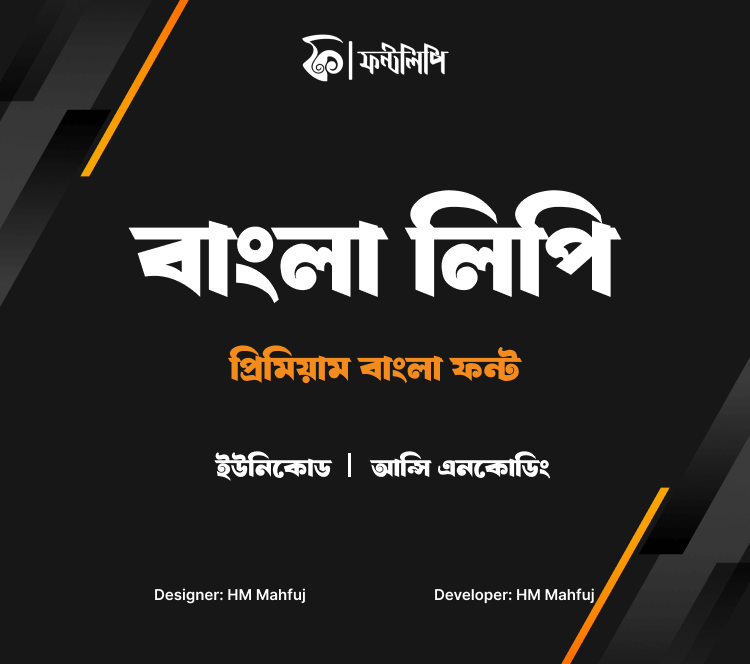
Bangla Lipi Font classic look এবং modern utility দুটোই ধরে রাখে। Serif-like subtle strokes থাকলেও readability modern apps-এ smooth। PixelLab-এ gebruikt করলে vintage yet crisp look মেলে।
Why it’s great for PixelLab / Mobile Design:
- Serif hint, readable texture
- Poster headline & description দুটোতেই useable
- Unicode support keeps mobile rendering safe
Best Use:
Formal event posters, announcement banners, quotes
Design Tip:
Background soft colour হলে text হারিয়ে যাবে না; contrast maintain করলে আরও eye-catching।
3. Amar Praner Modina
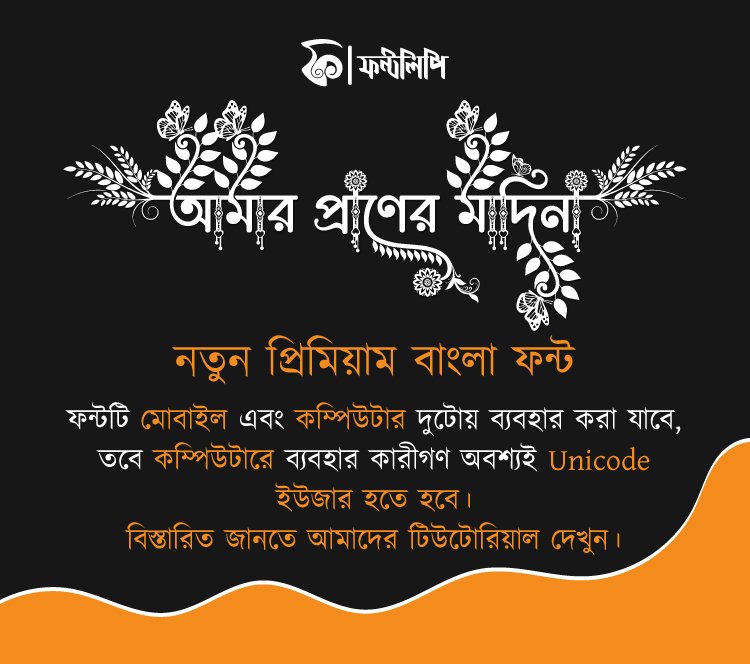
Amar Praner Modina একটু decorative ও expressive style Bangla font। Energetic stroke, unique curves এবং playful letterform-এর কারণে PixelLab-এ creative posters-এ ভালো লাগে।
Why it’s great for PixelLab / Mobile Design:
- Energetic feel
- Strong display presence
- Creative vibe
Best Use:
Festival posters, youth oriented graphics, artistic quote designs
Design Tip:
Short headline বা tagline-এ use করাই best; long text-এ use করলে readability কমে যেতে পারে।
4. Mahfuj Nazia
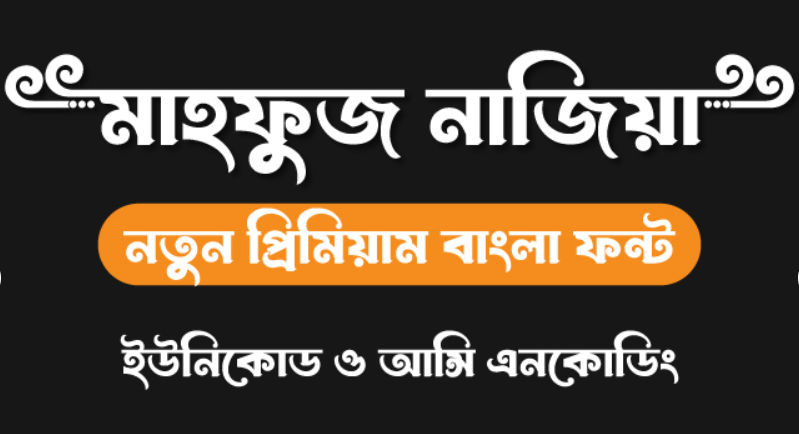
Mahfuj Nazia একটা elegant Bangla font যার strokes visually appealing এবং stylish edge আছে। PixelLab-এ use করলে feminine or upscale artistic posters-এ ভালো aesthetic মেলে।
Why it’s great for PixelLab / Mobile Design:
- Decorative aesthetics
- Good headline support
- Strong visual identity
Best Use:
Wedding posters, cultural program graphics, premium quote designs
Design Tip:
যেখানে visibility priority, সেখানে contrast সঠিকভাবে maintain করুন; high opacity colour রাখা ভালো।
5. Mahfuj Jorna Dhara (Premium)
Mahfuj Jorna Dhara একদম impactful design Bangla font, premium class। Stroke weight বেশি এবং visual impact খুব high, তাই poster headline-এ এটি attention grab করে। PixelLab-এ premium feel আনতে এটি ideal.
Why it’s great for PixelLab / Mobile Design:
- Maximum visual presence
- Works great in big headlines
- PixelLab-এ stylish posters-এর জন্য perfect
Best Use:
Headline only posters, event banners, product announcement
Design Tip:
Sub text-এ different cleaner font pair করুন—যাতে headline overshadow না করে पूरा design balance থাকে।
6. Hind Siliguri
Hind Siliguri Google Fonts-এর আরও একটি strong Unicode Bangla font। নরম rounded edges থাকলেও structure professional। PixelLab-এ use করলে modern & clean look পাওয়া যায়।
Why it’s great for PixelLab / Mobile Design:
- Rounded feel makes text friendly
- Works in posters and captions alike
- Proper spacing avoids glyph overlap
Best Use:
Social media caption, poster sub-heading, mobile UI text
Design Tip:
Black or dark green text colour দিয়ে pairing করলে contrast বেশি ভালো লাগে।
Conclusion
PixelLab এবং mobile design-এ আপনি যদি clean, readable এবং future-proof Bangla fonts চান, তাহলে নিচেরগুলো prioritise করতে পারেন:
✔ Noto Sans Bengali — Safe, simple, universal
✔ Hind Siliguri — Rounded and modern
✔ Mahfuj Jorna Dhara — High impact headlines
আর যারা creative posters বা festive design বানাতে চান, তাদের জন্য:
✨ Amar Praner Modina এবং Mahfuj Nazia অবশ্যই try করা উচিত।